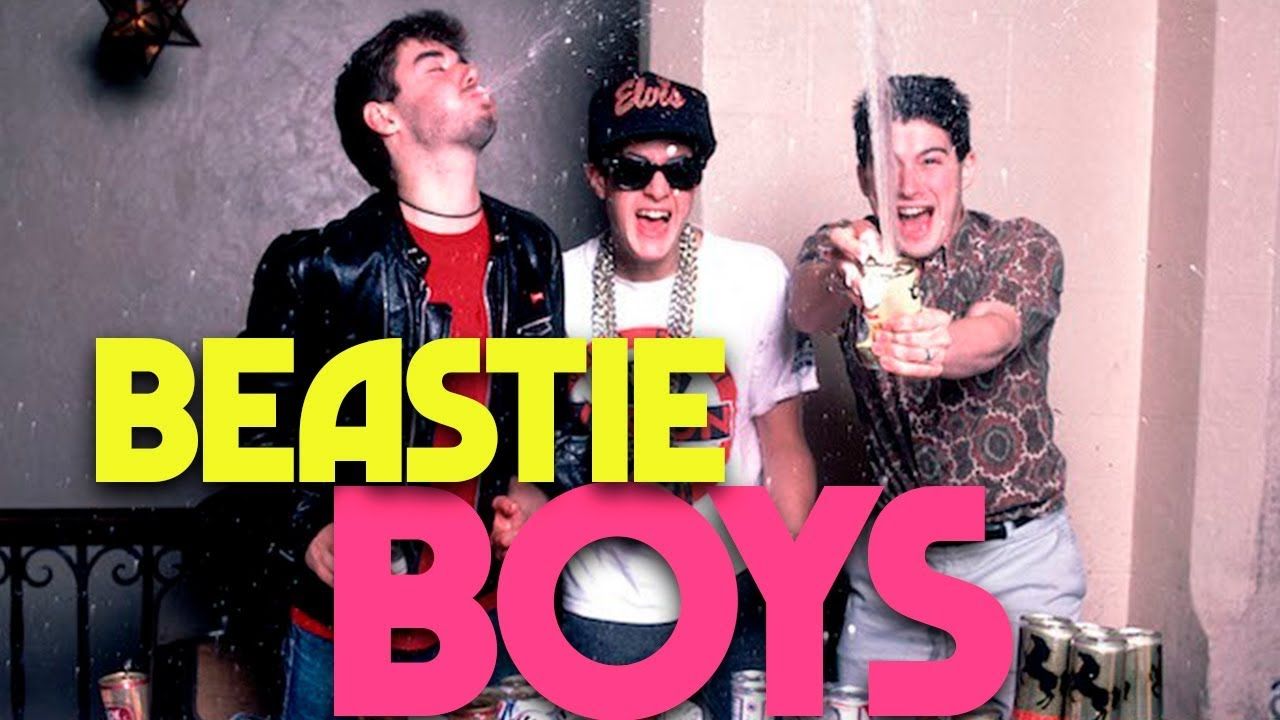
Foro de Tipografía Alguien Conoce la Tipográfia el 11.08.2019 a las 08:32 por ruyalxom · 1 comentario Seguir este tema Dejar de seguir este tema Alguien sabe que tipografia es esta, me gusta la letra A y me gusta para una comprarla, la busque en paginas como what font is pero no la he encontrado alguien la ubica? Comentar Me gusta
Marvin Visions (actualización de una tipo de los sesenta llamada Marvin)